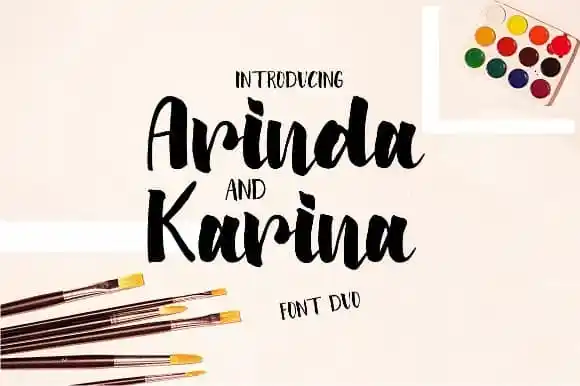
Arinda Brush Font
Arinda Brush Font é uma deliciosa fusão entre arte manual e modernidade pura. Introduzida pelo FLAMDE STUDIO, Arinda apresenta-se como um script brush font perfeitamente harmonizado com sua opção capa-a-capia, Karina. Este design exclusivo, cuidadosamente traçado para oferecer o melhor resultado possível, se tornou uma escolha ideal para vários tipos de projetos criativos. Suave e atraente na superfície, Arinda Brush Font se revela perfeito tanto para invitations memoráveis quanto para cartas de cumprimentos elaboradas. Também é perfeitamente adaptável a materiais de identidade corporativa, como cartões de visitas, ou até mesmo aplicações visuais, como cartazes e postais. Suavemente delicada em alguns momentos, poderosa e inegavelmente elegante nos outros, Arinda Brush Font está pronta para iluminar seus projetos de design com sua versatilidade única. Caracterizado por seu estilo a mão realista e sua aparência harmoniosa, Arinda oferece uma paleta perfeita de opções para quem deseja adicionar um toque único e elegante aos seus designs. Com sua facilidade em se adaptar às diversas necessidades de criação visual, essa fonte é uma excelente escolha para designers que desejam trazer novos elementos de beleza a seus projetos.